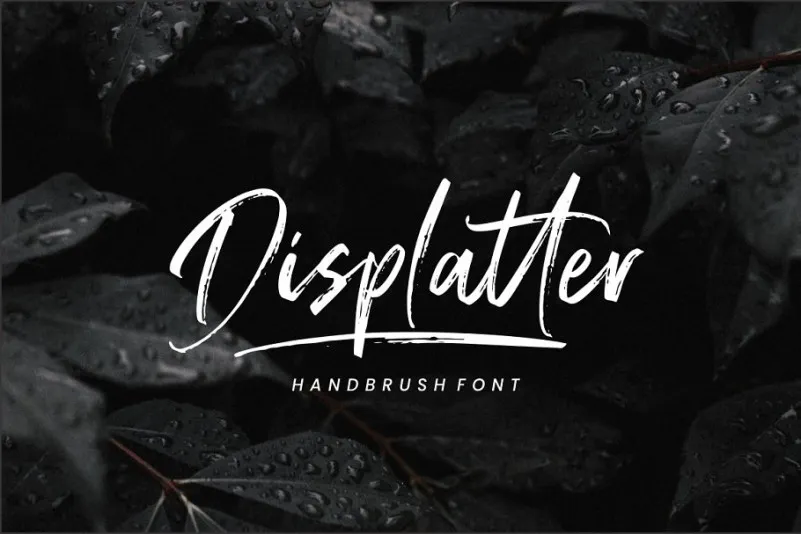
Displatter Handbrush Font – Download Grátis
Estou aqui para apresentar uma nova opção na categoria dos fonts script, a Displatter Handbrush Font. Essa é uma fonte moderna que evoca a essência da arte manual do desenho a mão, feita com pincel. Ideal para qualquer tipo de necessidade gráfica! A Displatter Handbrush Font é perfeita para criações como logos, convites, papéis de encomenda, designs de casamentos, posts nas redes sociais, anúncios, embalagens de produtos, design dos próprios produtos, etiquetas e até mesmo fotografias ou até mesmo eventos especiais. Esta fonte vem com toda a linha de letras maiúsculas e minúsculas, símbolos multilíngue, números e pontuação completa. Você está apto para usar essa font no seu próximo projeto gráfico!